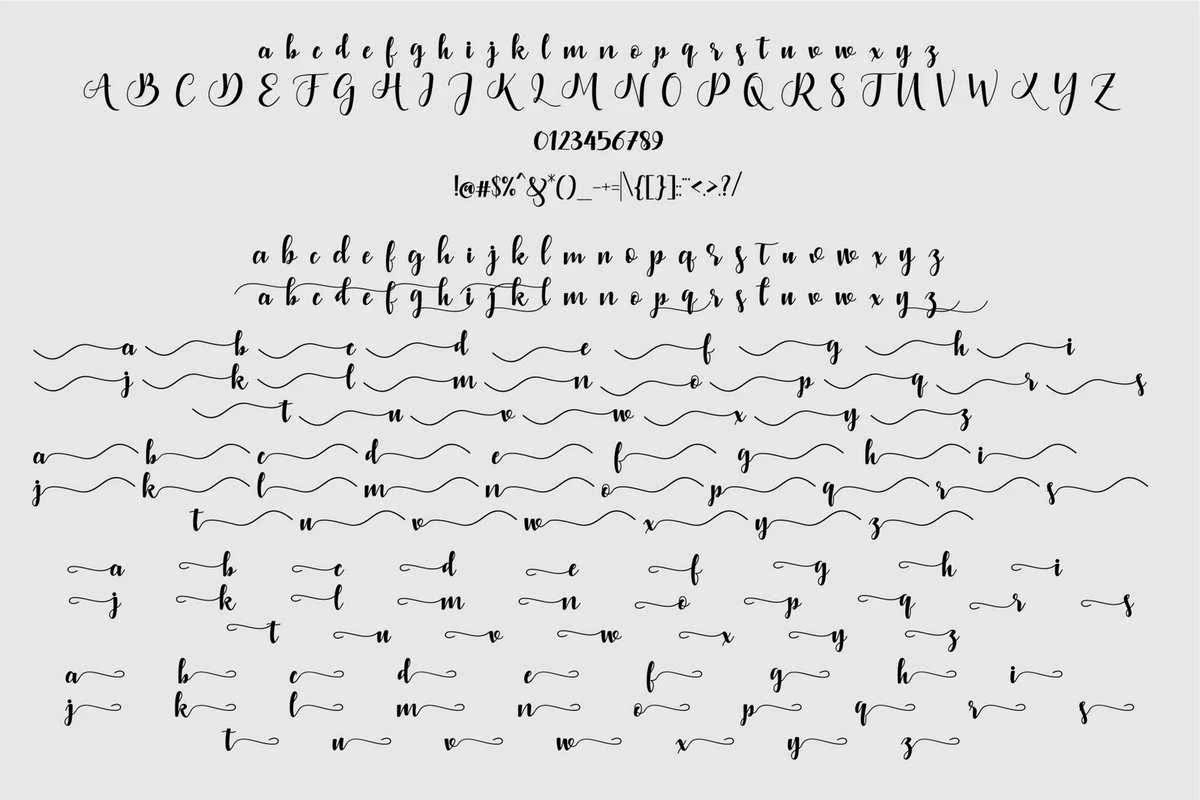
你好吗?我好极了!介绍,这是我们最新的产品,我们称之为MalmingFont。MalmingFont是一款全新的产品,每一位设计师都拥有如此甜美美丽的造型。AveryGoodMalmingFont Touseon:你好吗?我很高兴!介绍,这是我们最新的产品,我们称此产品为MalmingFont。MalmingFont是一款全新的产品,每一款产品都具有如此甜美和美丽的外观。AveryGoodMalmingFontOn: